ใครที่กำลังหาฟอนต์ภาษาอังกฤษสวย ๆ แนว Calligraphy ตัวเขียนด้วยพู่กันที่สามารถนำไปใช้ตกแต่งอาร์ตเวิร์คงานส่วนตัว งานนำเสนอ หรืองานอื่น ๆ เพื่อการศึกษา ทีมงานได้คัดสรร 10 ฟอนต์สวย ๆ มาแนะนำให้ชมกันค่ะ
แจก 10 ฟอนต์อังกฤษ แนว Calligraphy [ดาวน์โหลดฟรี]
1. Moving Skate [ดาวน์โหลดที่นี่]
2. Coaster Quake [ดาวน์โหลดที่นี่]
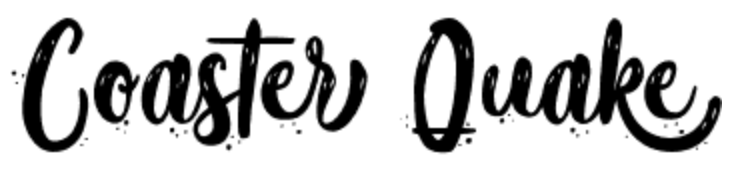
3. Slow Life [ดาวน์โหลดที่นี่]
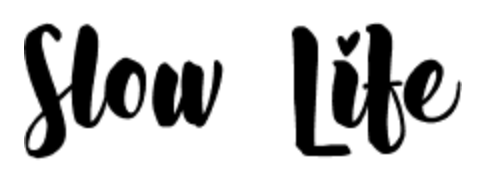
4. December Pastel [ดาวน์โหลดที่นี่]
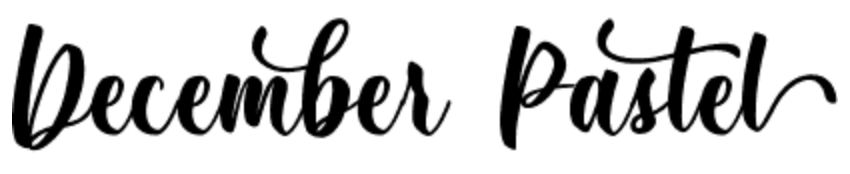
5. Antique Cherry [ดาวน์โหลดที่นี่]
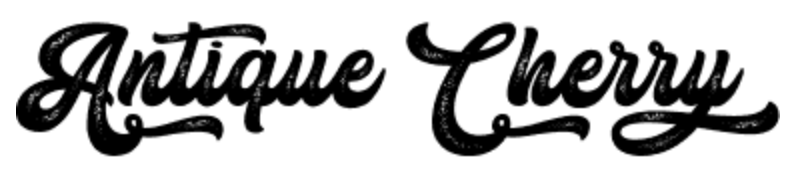
6. Play Day [ดาวน์โหลดที่นี่]
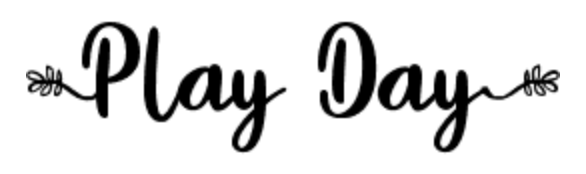
7. December Pastel [ดาวน์โหลดที่นี่]
8. Quark Cheese [ดาวน์โหลดที่นี่]
9. Inkland [ดาวน์โหลดที่นี่]
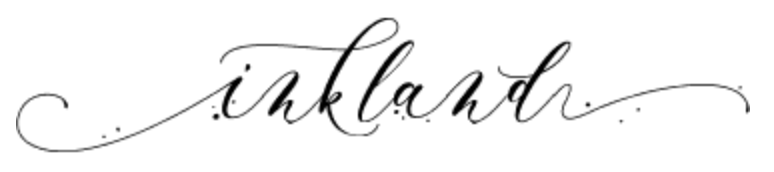
10. Absolute Pink [ดาวน์โหลดที่นี่]